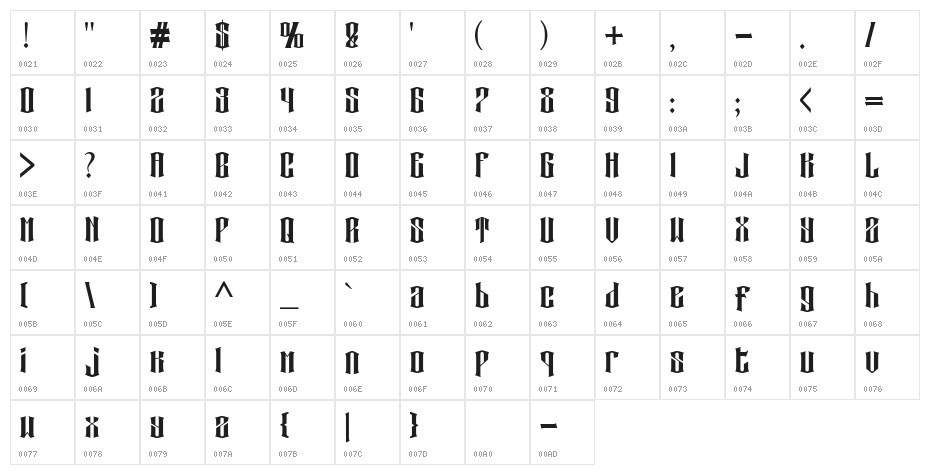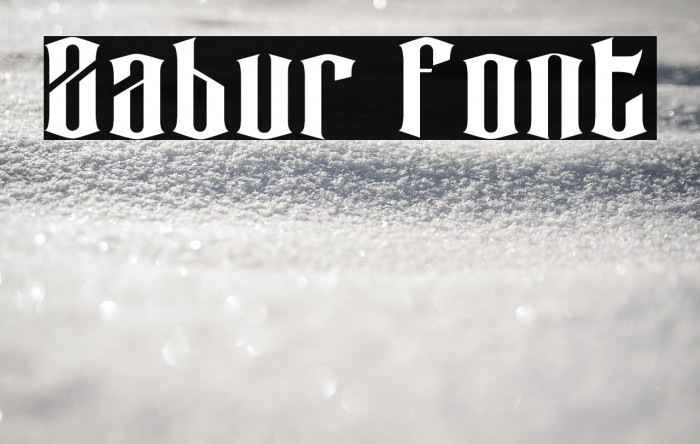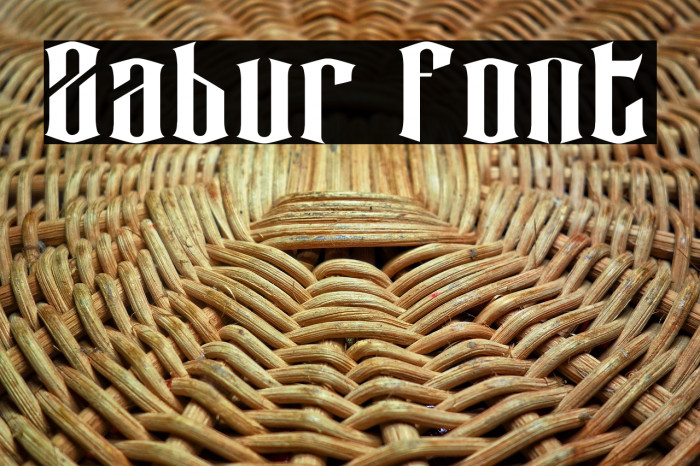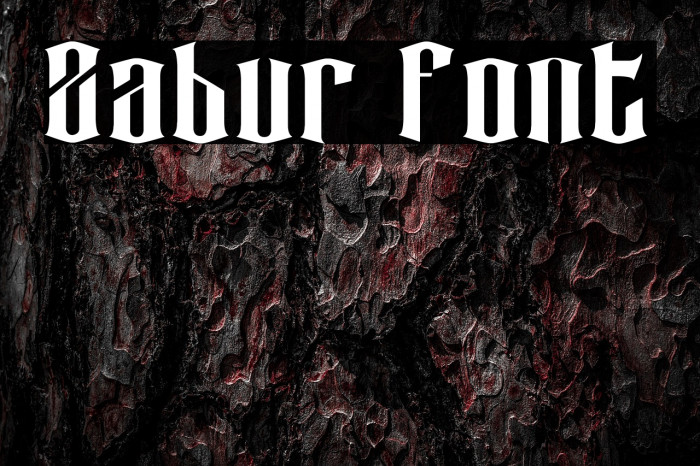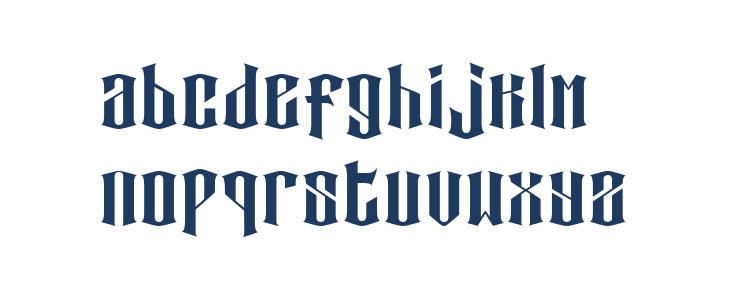
Zabur Font
✎ Gothic
| Kategorien | Gothic |
| Gesamtstil | Vintage |
| Vorgeschlagene Projekte | Ideal for historical-themed designs, gothic posters, book covers, and branding that requires a traditional and strong aesthetic. |